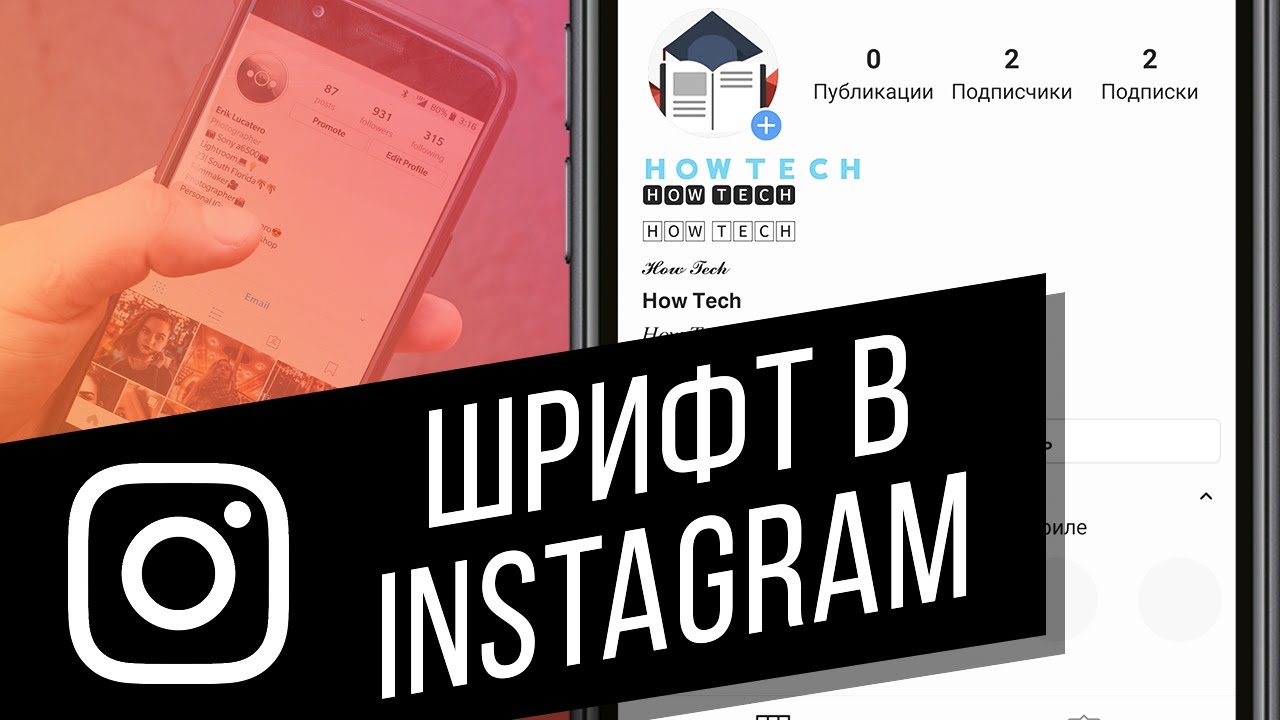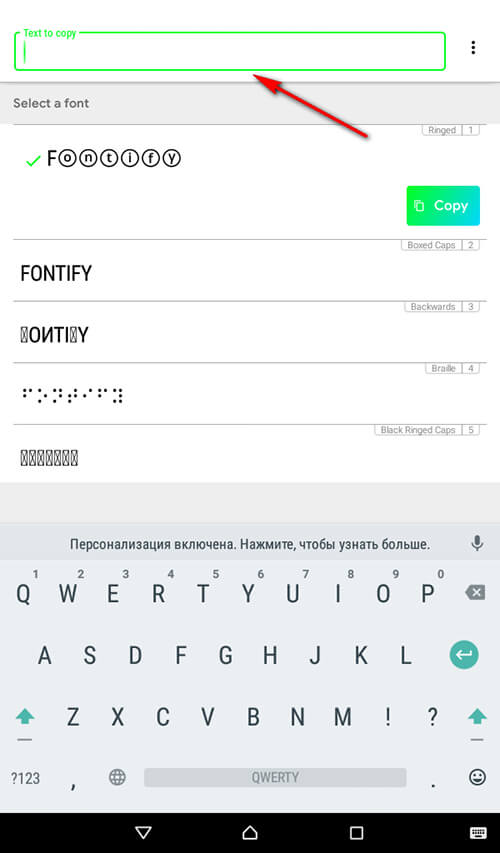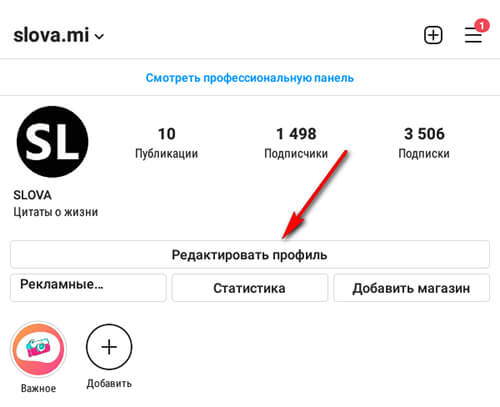
Как сделать красивый шрифт в Инстаграме, не потеряв текст при озвучивании
Декоративный текст для имени, БИО или подписи в Инстаграме по-прежнему создают вне соцсети: обычные буквы преобразуют, копируют и вставляют в нужное поле. Имя и имя пользователя можно изменить через настройки профиля или Центр аккаунтов — этот порядок подтверждает справка Instagram об изменении профиля.
Так называемый красивый шрифт — обычно не шрифт, установленный в Instagram, а строка из визуально похожих символов Unicode. Она остаётся копируемым текстом, однако экранная программа доступа может произнести названия начертаний между буквами или вовсе пропустить отдельные слова. Поэтому для оформления лучше преобразовывать короткий акцент, а важные сведения оставлять обычными символами.
Что генератор меняет на самом деле
Настоящий шрифт задаёт внешний вид символов, не подменяя сами буквы. Большинство генераторов для социальных сетей работает иначе: например, обычная латинская A заменяется самостоятельным математическим, рукописным или готическим знаком, который похож на неё внешне, но имеет другой код.
Технический отчёт консорциума Unicode относит такие знаки к математическим алфавитно-цифровым символам и прямо указывает, что они предназначены для математических и технических обозначений, а не для обычной речи. Документ также предупреждает: конкретный вид символа зависит от доступных в системе шрифтов, поэтому полагаться на одинаковое отображение везде нельзя.
Именно этим объясняются характерные ограничения генераторов. Для латиницы существует много готовых математических начертаний, тогда как сопоставимого набора стилизованной кириллицы нет. Русское слово может остаться без изменений, превратиться в смесь разных знаков или получить оформление только за счёт добавочных символов и диакритики.
Подмена влияет не только на внешний вид. Для программы, поиска или буфера обмена стилизованная буква и похожая на неё обычная буква могут быть разными символами. Поэтому декоративное написание имени, хештега или адреса нельзя считать полным эквивалентом исходной строки.
Как добавить декоративный текст в имя или БИО
Устанавливать специальную клавиатуру необязательно: достаточно браузерного генератора Unicode-текста, который показывает результат до копирования. Такому сервису не нужен пароль от Instagram — преобразование строки и работа с буфером обмена не требуют доступа к аккаунту.
1. Введите в генератор короткий фрагмент — например, имя, рубрику или одно слово для акцента.
2. Выберите вариант, который легко прочитать без сравнения с оригиналом, и скопируйте его.
3. Откройте свой профиль в Instagram и перейдите к его редактированию.
4. Вставьте строку в отображаемое имя или БИО и сохраните изменения.
5. Заново откройте профиль в приложении и браузере, чтобы проверить символы, пробелы и переносы.
Отображаемое имя и имя пользователя выполняют разные задачи. Имя находится в шапке профиля и допускает небольшой визуальный акцент. Имя пользователя входит в адрес аккаунта и используется в упоминаниях, поэтому его лучше оставить простым и легко набираемым.
В БИО декоративным можно сделать короткий заголовок или разделитель. Профессию, город, способ связи, условия заказа и другие сведения, ради которых открывают профиль, безопаснее писать обычными символами. Если Instagram не принимает преобразованную строку в выбранном поле, искать обходной способ не стоит: поле может ограничивать допустимые знаки.
Как оформить подпись к публикации
Для подписи действует та же схема: подготовьте строку в генераторе, скопируйте её и вставьте при создании или редактировании публикации. Необычные символы уместнее использовать как короткий заголовок, а не как замену всему тексту.
Перед публикацией проверьте цифры, знаки препинания, пробелы и переносы. Генератор может обработать только часть строки, из-за чего рядом окажутся символы из разных наборов. Хештег, набранный похожими декоративными буквами, также может не совпасть с обычным вариантом на уровне кодов.
Если нужен настоящий шрифт поверх фотографии, истории или видео, задачу решает встроенный редактор соответствующего формата либо графическое приложение. Тогда надпись становится визуальным слоем изображения или ролика, а не частью текстовой подписи. Существенную информацию полезно продублировать обычным текстом, чтобы она не зависела только от изображения.
Почему такой текст мешает экранным программам доступа
Экранная программа доступа обрабатывает код каждого символа, а не оценивает строку как зрячий читатель. Поэтому то, что выглядит как жирный курсив, может быть озвучено как последовательность математических знаков с повторяющимися обозначениями начертания.
Рекомендации RNIB по доступности соцсетей предупреждают, что экранные программы могут произносить «жирный» или «курсив» до либо между буквами, а некоторые пропускают целые слова. Организация советует использовать стандартные символы, чтобы основное содержание оставалось понятным.
Для профессионального аккаунта это особенно существенно. Если декоративными знаками набраны имя компании, профессия или контакты, препятствие возникает именно там, где человек пытается понять назначение страницы или связаться с её владельцем.
Что оставить обычным текстом
Безопасный компромисс — преобразовать одну короткую строку и не трогать сведения, которые нужно найти, скопировать или набрать вручную. От варианта лучше отказаться, если буквы приходится угадывать, кириллица перемешалась с латиницей или вместо части знаков появились пустые прямоугольники.
• Оставляйте обычными символами имя бренда, профессию, контакты и адрес сайта.
• Не заменяйте знаки в имени пользователя и значимых хештегах похожими символами.
• Не смешивайте несколько декоративных начертаний в одной строке.
• Сохраните исходный вариант БИО в заметках перед редактированием.
• Проверьте, можно ли прочитать результат без подсказки и сравнения с оригиналом.
На личной странице допустимо экспериментировать шире, если владелец принимает ограничения поиска и доступности. Для профессионального профиля разумнее ограничиться небольшим акцентом в имени или БИО: так оформление меняется, а ключевой текст остаётся читаемым и копируемым.